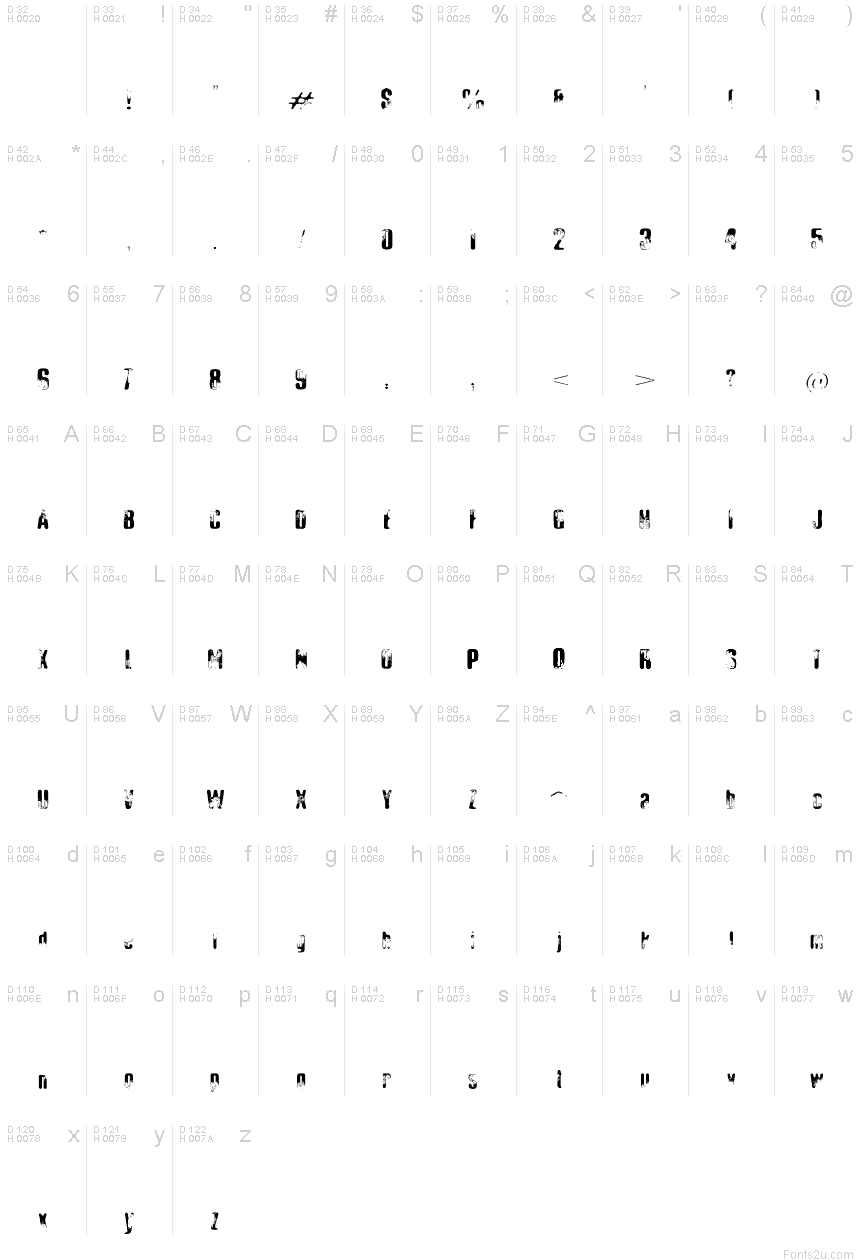
Elliot's Bad Day 4 to darmowy krój grunge, który wygląda, jakby został przeciągnięty po betonie i zostawiony na deszczu. Ciężkie, zaokrąglone litery z rodziny Elliot's Bad Day mają wyszarpane krawędzie i zachlapane, tuszowe tekstury, które sprawiają wrażenie surowych i nieco obłąkanych. Odstępy pozostają zaskakująco czytelne, więc zyskujesz maksymalny chaos, nie tracąc przekazu.
Dzięki Elliot's Bad Day 4 Twoje horrory, plakaty na koncerty punkowe, fanziny, tytuły gier, okładki albumów i miniatury na YouTube zyskają klimat totalnego rozpadu. Ten darmowy font najlepiej sprawdza się w dużych rozmiarach, gdzie widać jego ziarniste, kruszące się detale. Spróbuj połączyć go z czystym, geometrycznym krojem bezszeryfowym w tekście głównym, aby utrzymać układ w ryzach, podczas gdy nagłówek będzie krzyczał.
Elliot's Bad Day
4